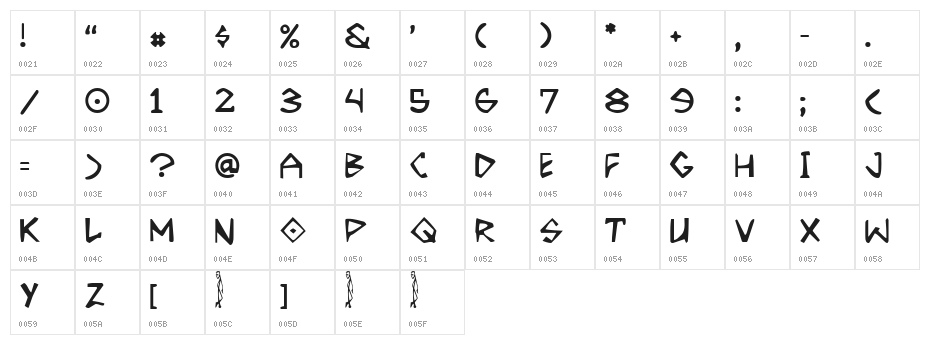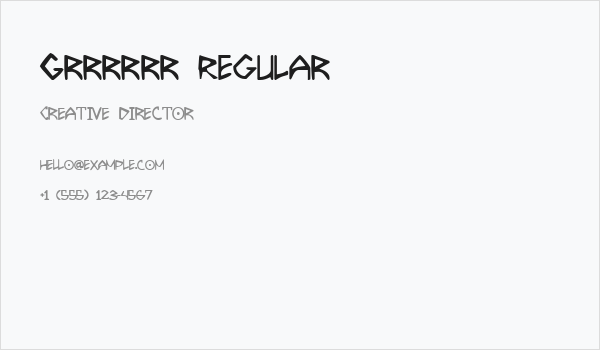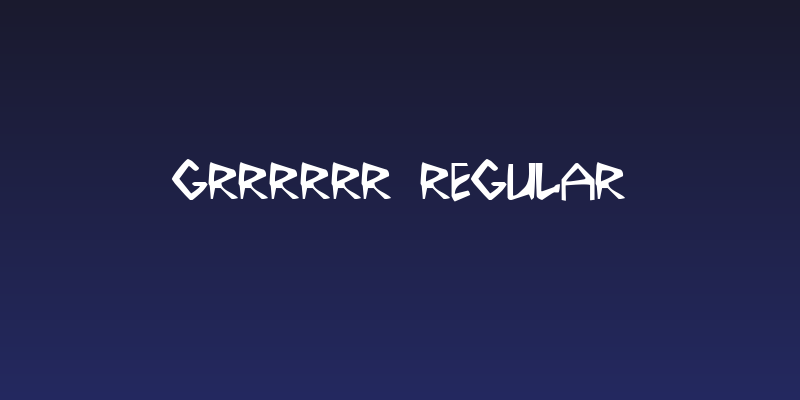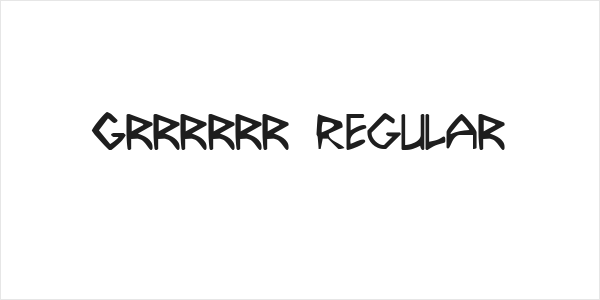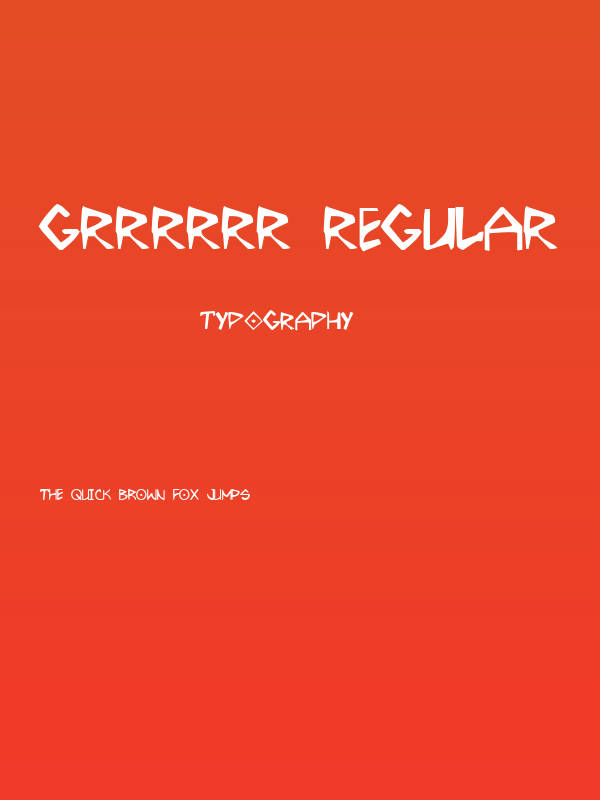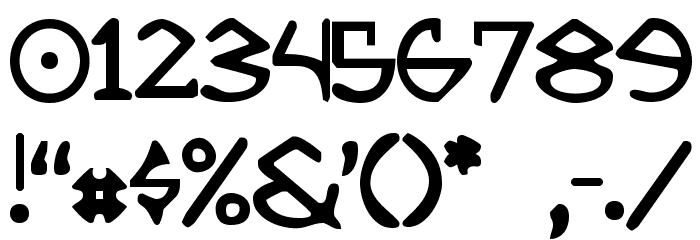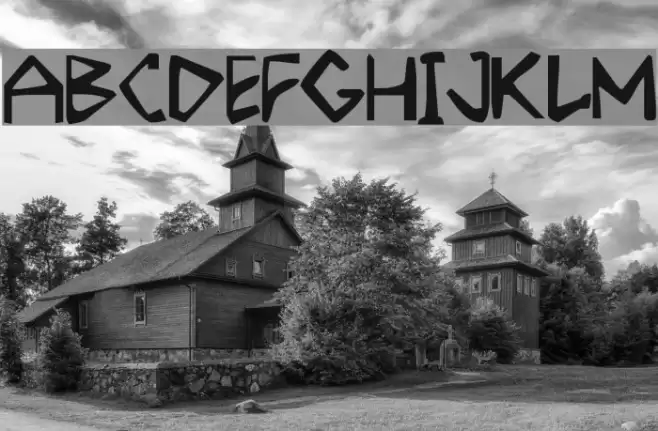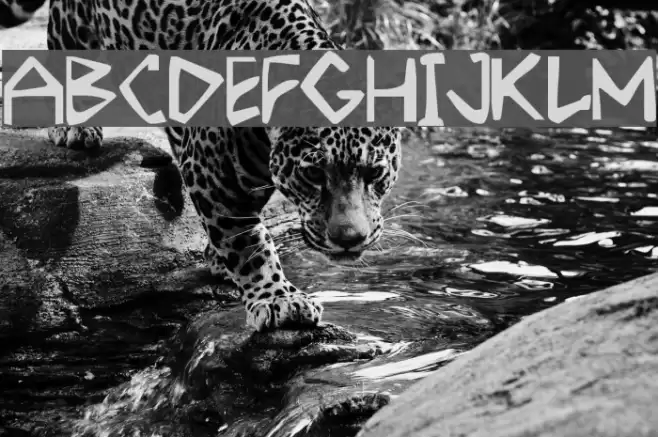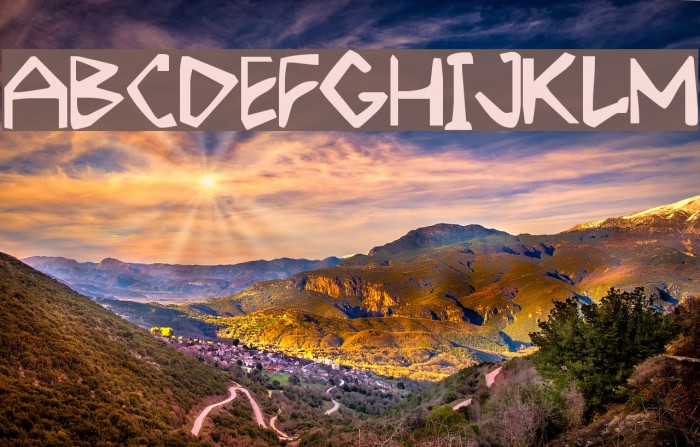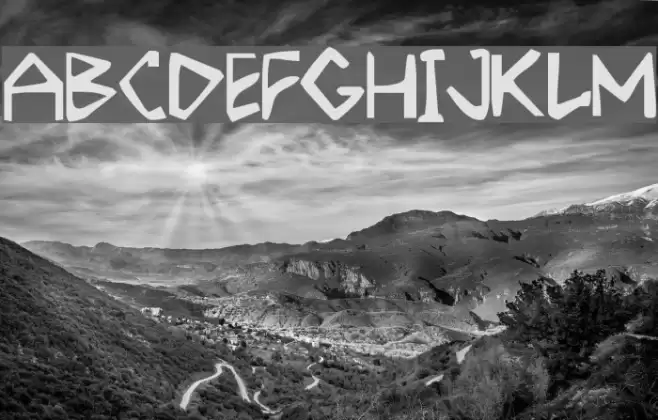
Grrrrrr Regular Font
| Gesamtstil | Playful, Bold, Dynamic |
| Vorgeschlagene Projekte | Ideal for comic books, children's books, playful branding, and eye-catching headlines. |